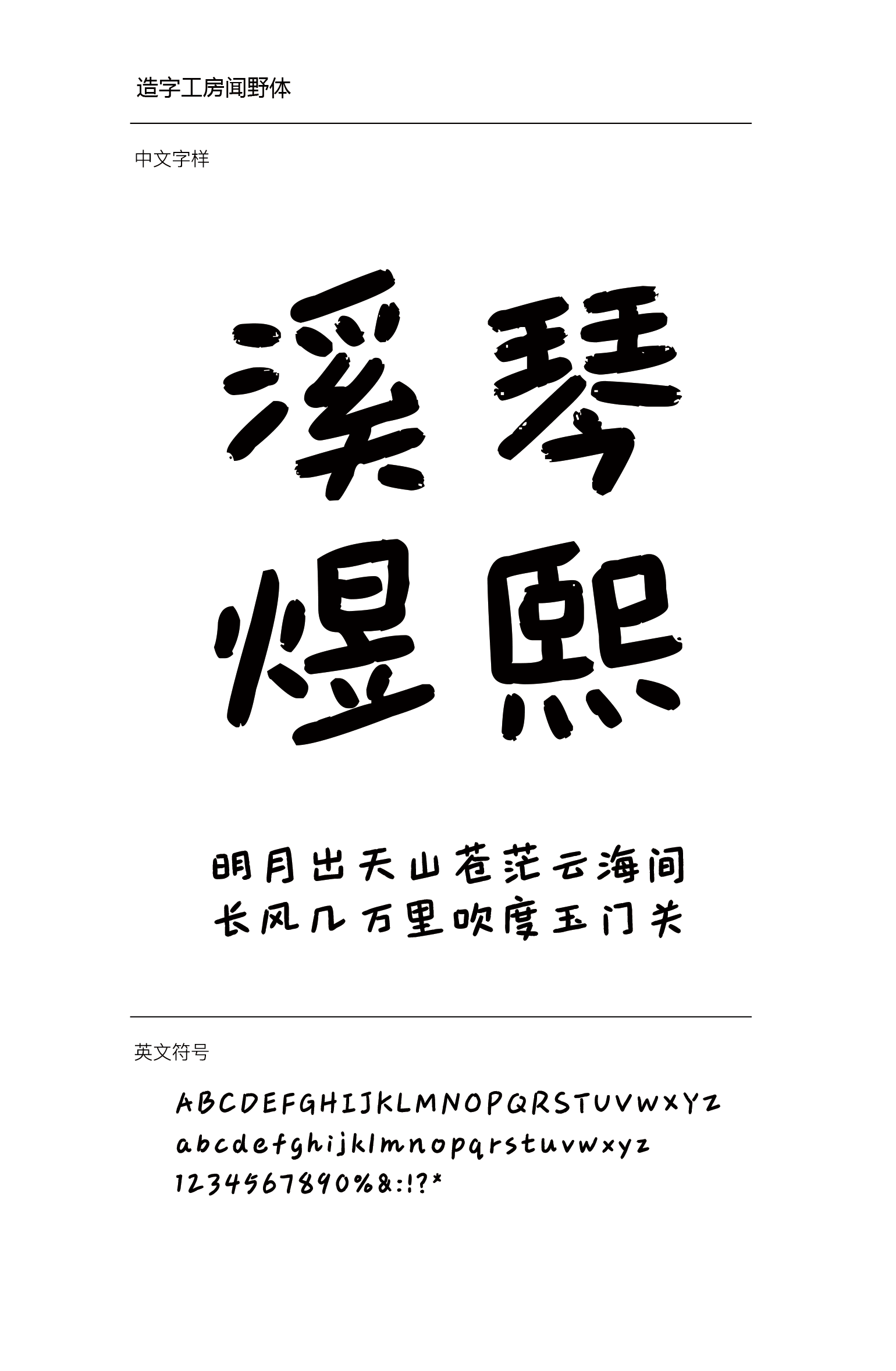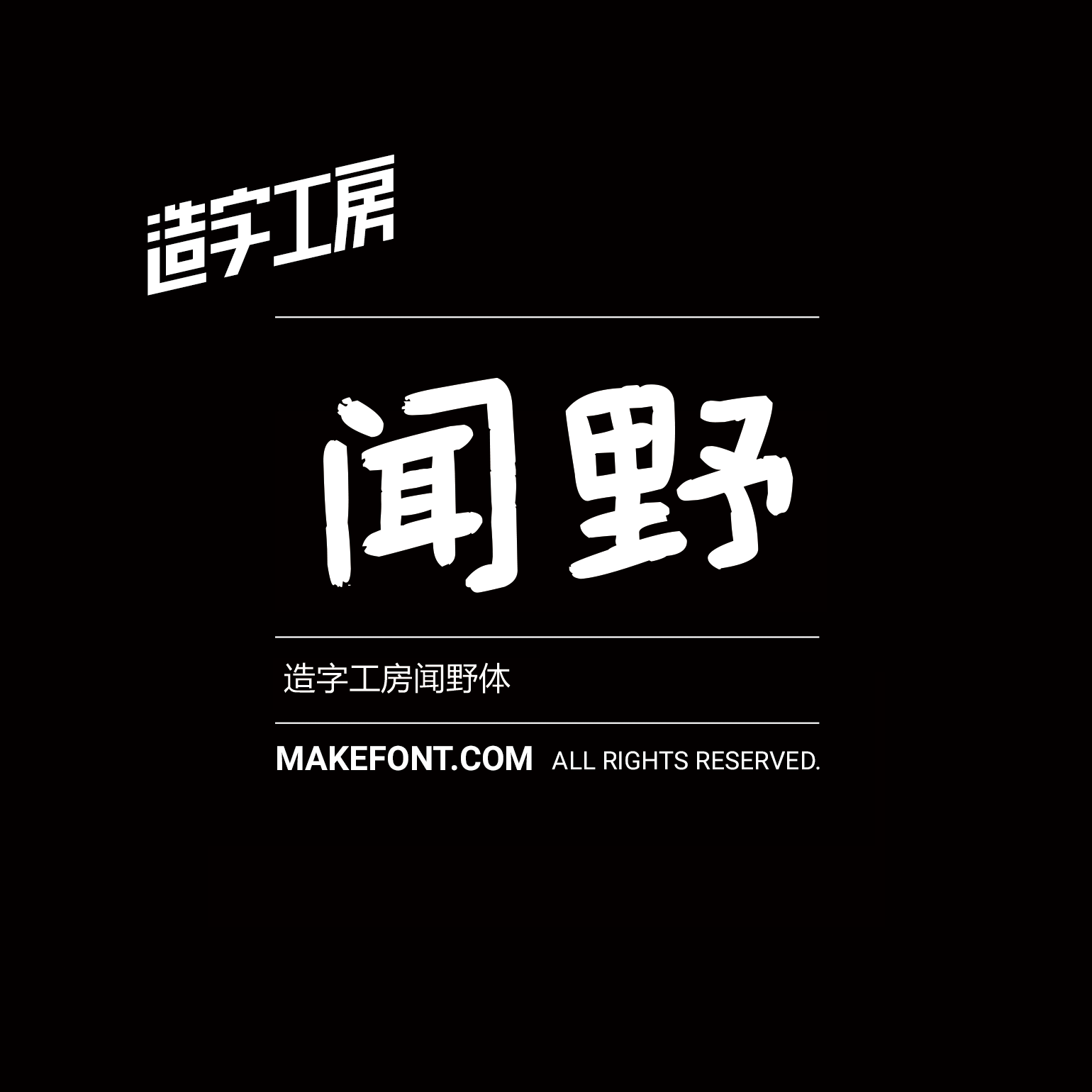
造字工房闻野体设计说明
造字工房闻野体,笔画柔和,结构舒展灵活,风格自然隽永,运笔流畅活泼,排版时节奏轻快,增加了字体洒脱、松弛的氛围感,是一款辨识度高、风格出众的字体。本字体为简体字库,采用OpenType/CID格式,Adobe-GB1-5编码。基于中华人民共和国GB2312-80字符集标准,另按需添加101个汉字。共收容字数6864CJK汉字,ASCII常用字符100个。